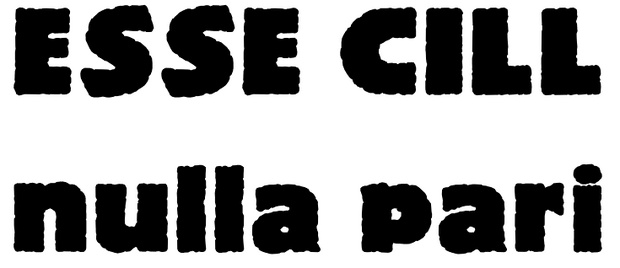
Ersatz für Publicity Gothic gesucht (ohne raue Kanten)
ich suche eine ähnliche Schrift wie die "Publicity Gothic", allerdings ohne die rauen Kanten. Mir kommt sie bekannt vor, ich komme aber leider nicht drauf.
Ähnlich, jedoch mit glatteren Kanten, ist die Block von Berthold.
Danke, ich denke, die ist ähnlich genug. Als Alternative habe ich sonst gerade noch die "Berlinsans" gefunden.